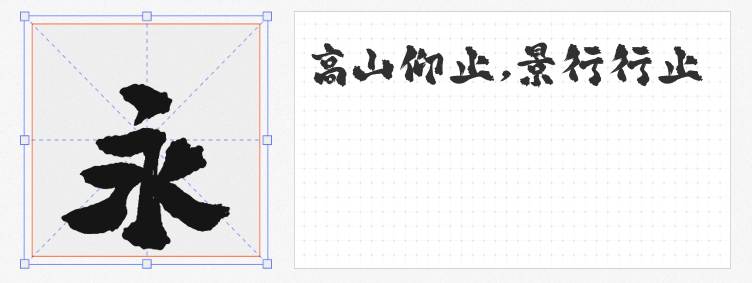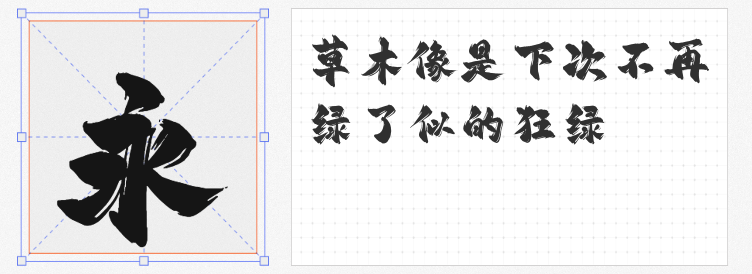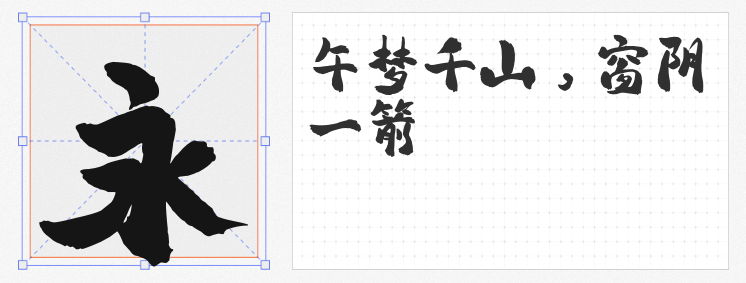
国潮设计浪潮中,手写字体以笔墨的温度与力量,赋予作品独特的文化基因。今天推荐的四款免费商用字体,皆以毛笔书法的磅礴气韵为骨,为品牌视觉注入东方美学的灵魂。
1. 平方赖江湖怀古体
这款字体以古法毛笔为魂,起笔收笔的粗厚线条如刀刻斧凿,遒劲笔触间流淌着千年文脉的厚重感。笔画统一中暗藏微妙变化,既有碑刻的刚劲,又兼得行书的洒脱,适合历史、文创、茶酒类品牌的标题设计,一撇一捺皆成岁月注脚。
2. 平方赖江湖飞扬体
平方赖江湖飞扬体以“飞白”为视觉符号,干笔擦痕与浓墨重彩交织,形成强烈的虚实对比。笔锋游走间似有风雷之势,既保留书法的筋骨,又赋予现代设计的动态张力。无论是海报标题、影视字幕,还是国风文创包装,其肆意挥洒的笔触都能瞬间点燃视觉焦点。
3. 平方赖江湖琅琊体
平方赖江湖琅琊体以毛笔笔刷的天然肌理为特色,粗犷线条中暗藏细腻的墨色层次,仿佛能看见笔锋在宣纸上翻卷的轨迹。其字形结构疏密有致,既有碑学的雄浑,又兼得帖学的灵动,尤其适合武侠、国潮服饰、非遗文化等领域的视觉表达,一纸墨香写尽江湖豪情。
4. 黄凯桦律师手写体
由AI生成的这款手写体,以现代科技复刻传统书写的温度。笔画刚柔并济,既有毛笔书法的筋骨,又因AI的微调而更显规整易读。其字形介于行书与楷书之间,既有文人雅士的从容,又暗含现代设计的理性,适合法律、文化、教育类品牌的标题设计,以科技之力传递人文温度。
四款字体,或如古碑沉雄,或似飞白凌空,或留笔刷江湖,或借AI焕新,皆以手写之魂诠释国潮设计的磅礴气韵。它们不仅是视觉工具,更是文化载体,让每一笔墨痕都成为品牌与受众对话的桥梁。